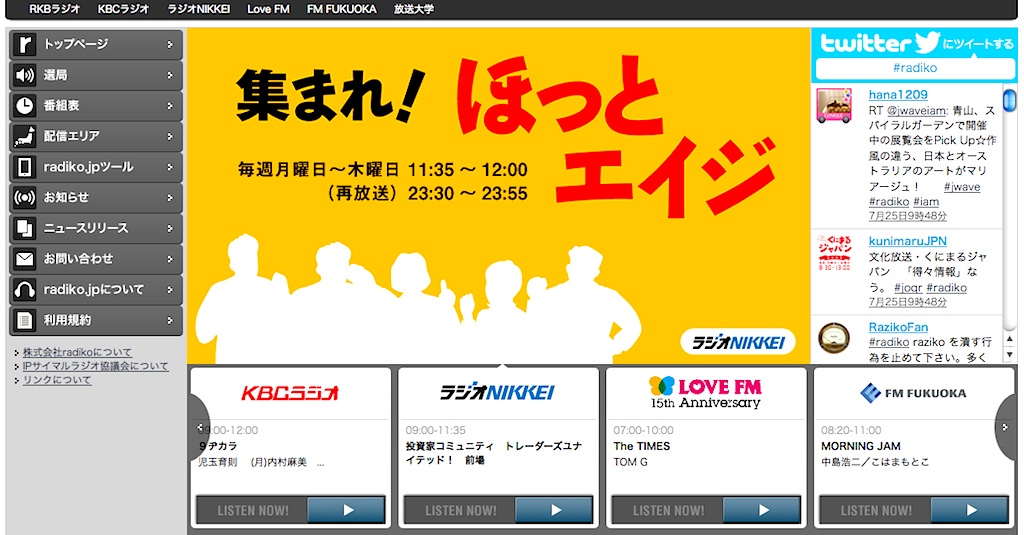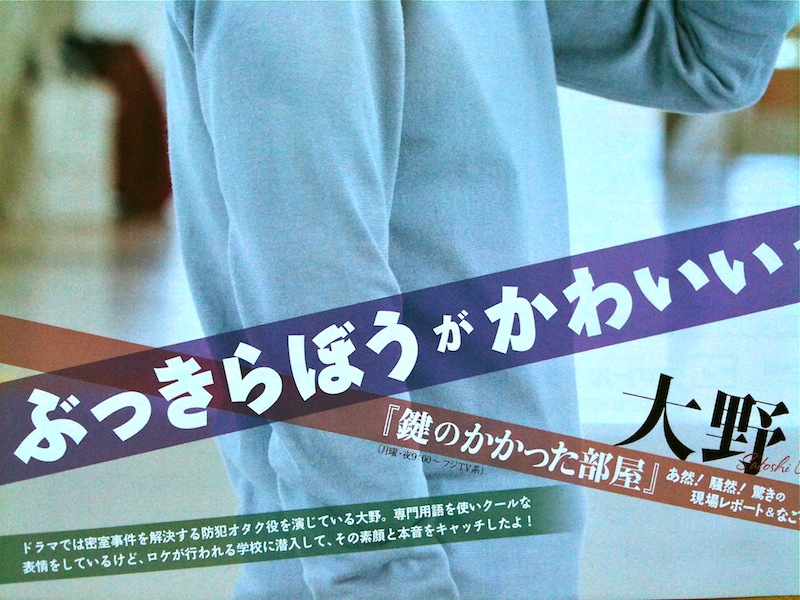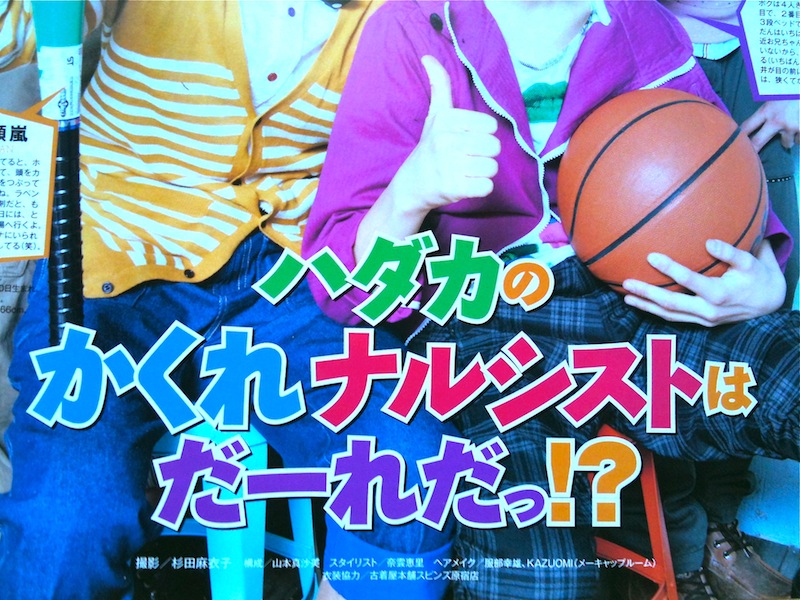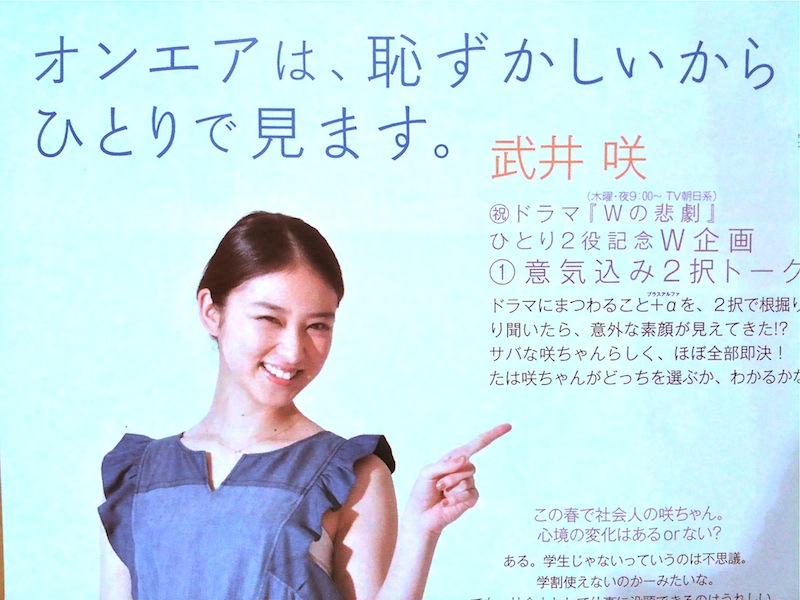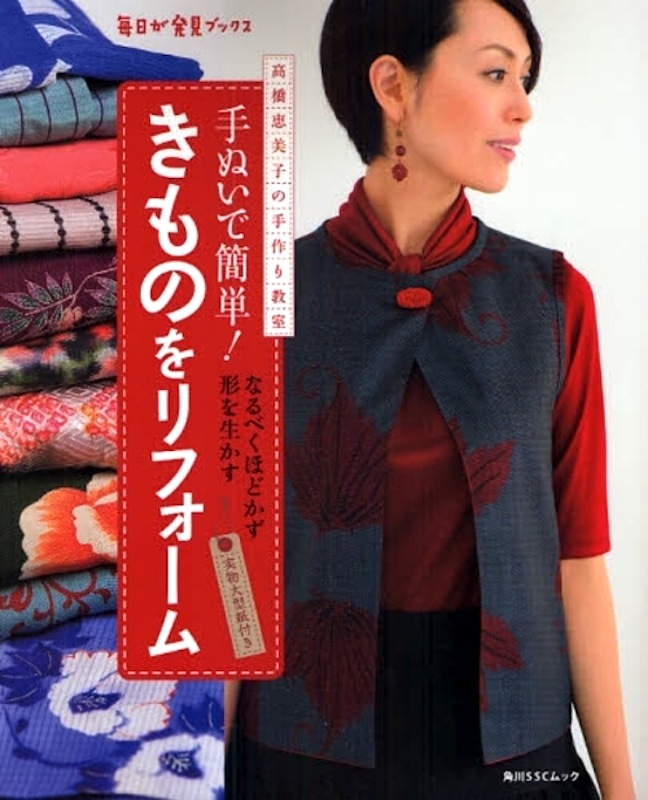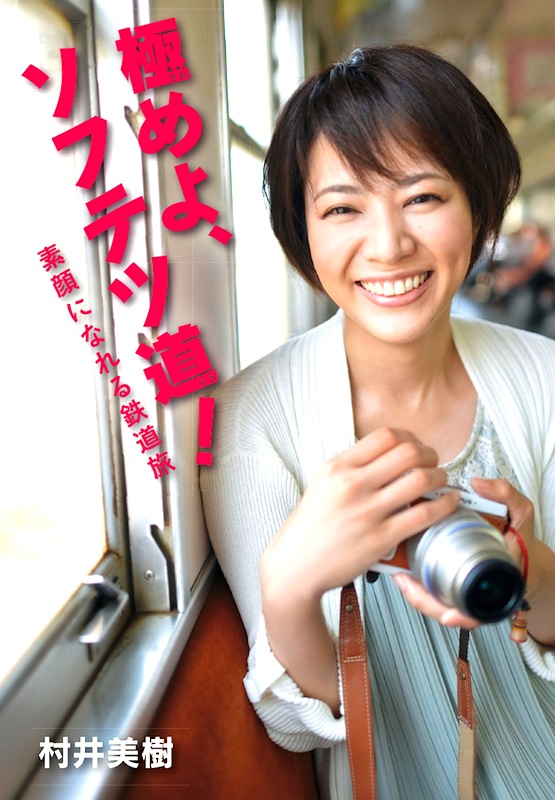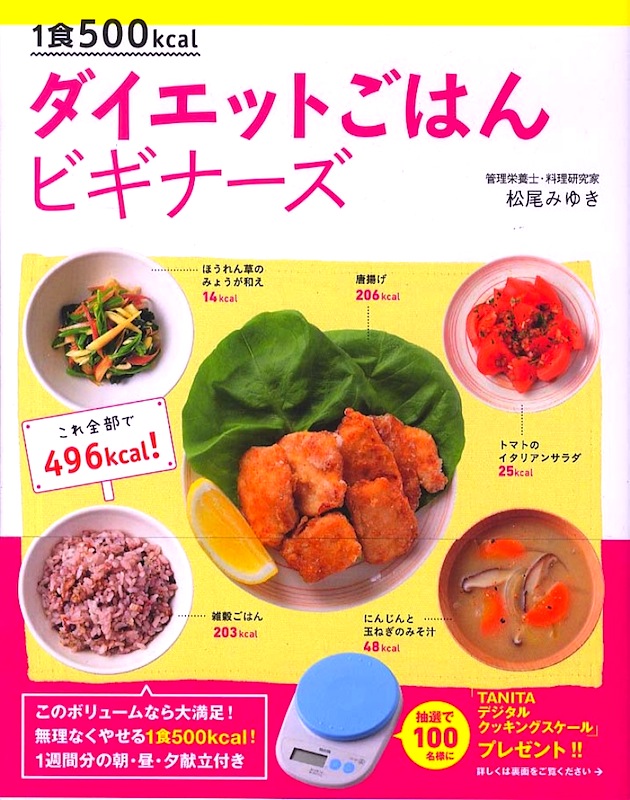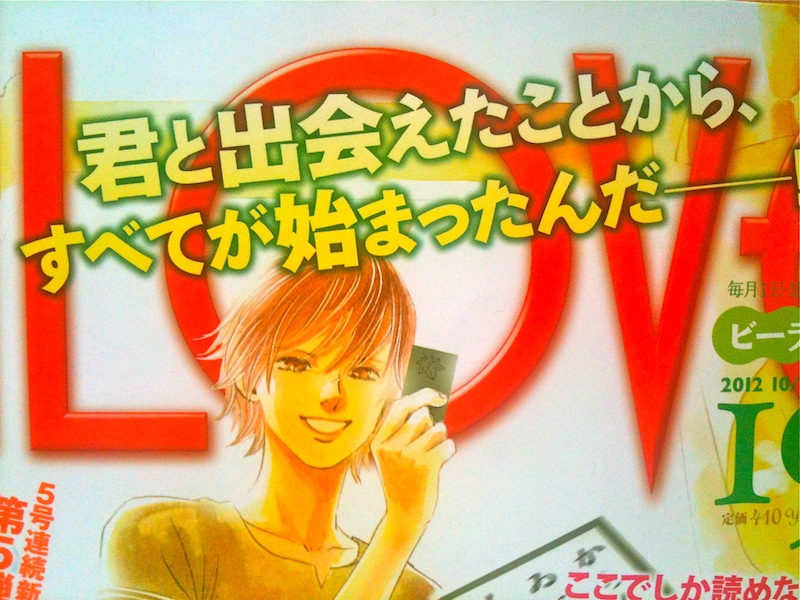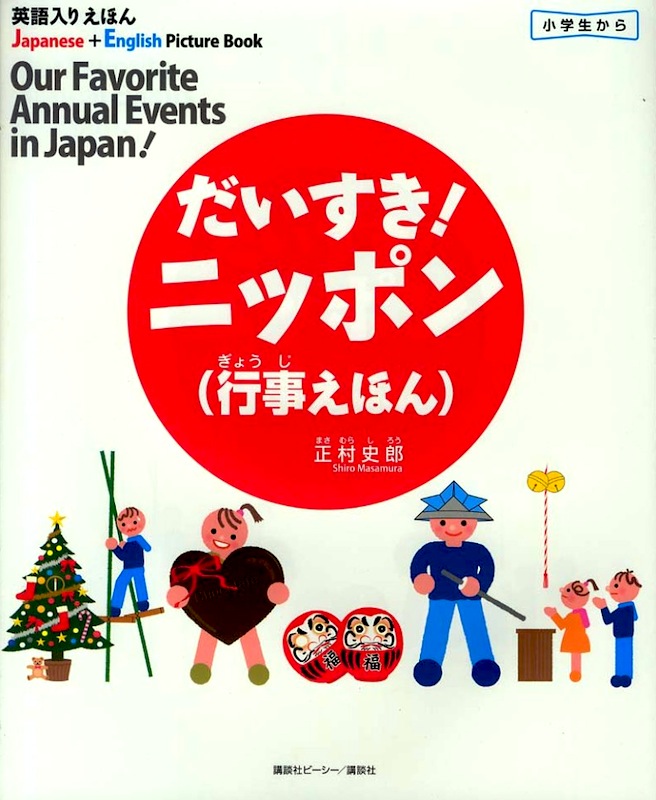
本の表紙  さとうゆたか  2014年8月28日(木) 16:44
書名:さんすうサウルス
著者:ミッシェル・マーケル 絵:ダグ・クシュマン
翻訳:はいじま かり
発行:福音館
本の表紙  さとうゆたか  2014年8月10日(日) 9:03
書名:そうちゃんはおこってるんだもん
著者:筒井頼子 文 / 渡辺洋二 絵
発行:福音館書店
本の表紙  さとうゆたか  2014年7月3日(木) 17:07
書名:なぜあなたは「愛してくれない人」を好きになるのか
著者:二村ヒトシ
発行:イースト・プレス
なぜか漢字書体が太い。
なにか意図があるのだろうか…。よく判らん。
写真コンテストのロゴ  さとうゆたか  2014年7月3日(木) 8:20
荒川区・文京区・千代田区を対象とした写真コンテストの応募チラシから。
サマーソング特集  takumi  2014年7月3日(木) 3:33
音楽ダウンロード購入サイト『mora』で墨東書体を見つけました。
「SUMMER SONG SPECIAL」の文字でわかりましたが、『墨東ルイカ』のようです。
たしかに、墨東ルイカですね。
本の表紙  さとうゆたか  2014年5月26日(月) 16:36
書名:ぷにんぷかあさん 今日も育児日和
著者:前川さなえ
発行:マイナビ
絵本  さとうゆたか  2014年5月8日(木) 14:02
これは墨東ルイカですね。
フォントワークスやモリサワの墨東とは「ま」の形が違います。
書名:おつきさまはまあるくなくっちゃ!
著者:ふくだじゅんこ
発行:大日本図書
雑誌の記事  さとうゆたか  2014年4月17日(木) 16:14
見出し部分は、すべて墨東ですね。
本の表紙  さとうゆたか  2014年4月8日(火) 21:57
書名:きえたぐらぐらのは
著者:コルネーリア・フンケ, ケルスティン・マイヤー
発行:WAVE出版
絵本  さとうゆたか  2014年4月1日(火) 16:42
書名:あ〜んぱくっ
著者:せきゆうこ
発行:小学館